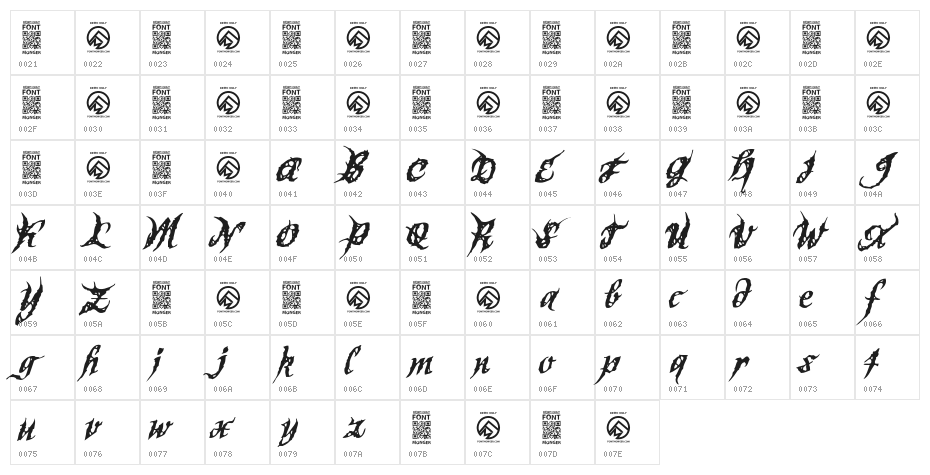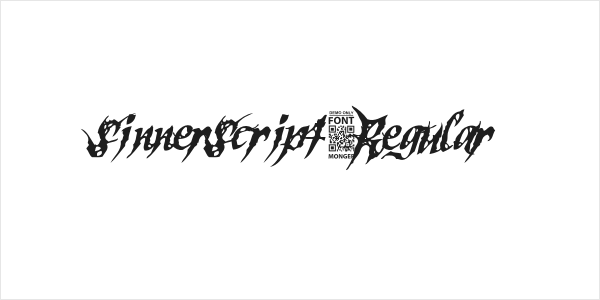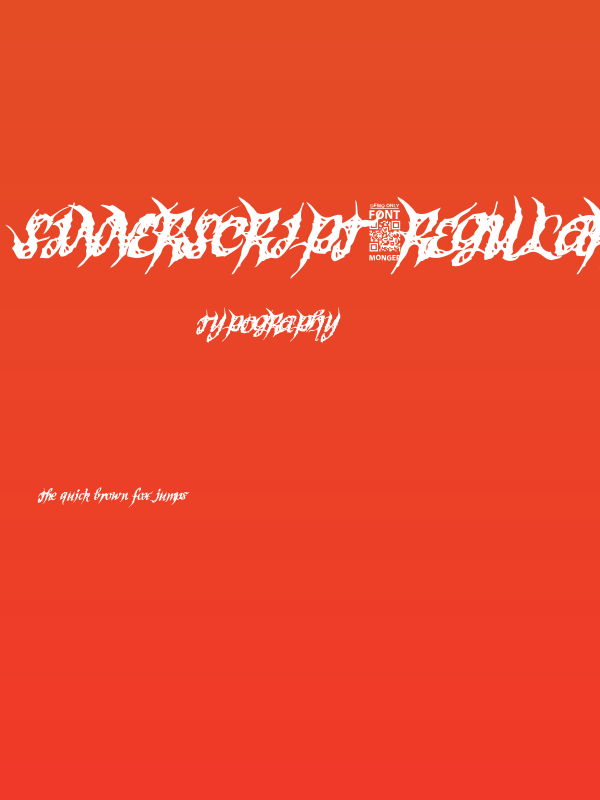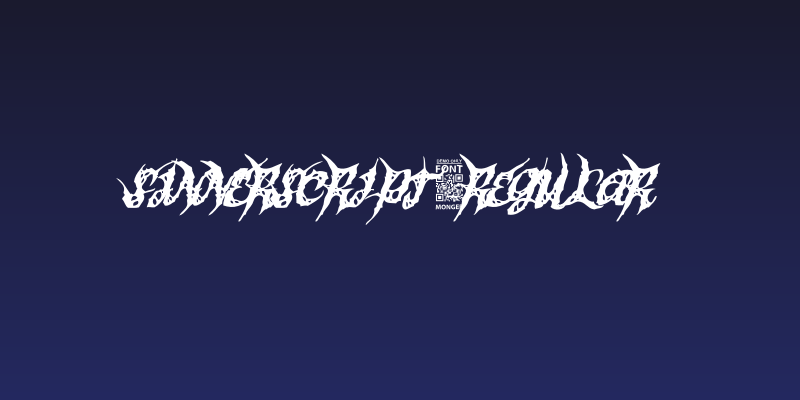
SinnerScript-Regular Font
| Anwendungsfall | Logos, Headlines |
| Vorgeschlagene Projekte | Ideal for tattoo designs, band logos, album covers, and edgy branding projects. |